안병국의 웹타이포그래피 – 헤드카피와 서브카피의 관계.1
세련된 디자인이라 함은 앞에서도 언급했듯 전체가 아름다운 조화를 이룰 때 만들어진다. 영화에서처럼 디자인에도 주연과 조연 엑스트라가 등장하기 마련인데 조연과 엑스트라는 주연을 더욱 돋보이기 위해 희생할 줄 알아야 하며, 주연의 부족한 부분을 메워 줄 수 있을 때 좋은 디자인이 만들어지는 것이다. 그러나 서로가 주연처럼 경쟁한다면 그로인해 사용자의 시선은 분산될 수밖에 없으며 혼란스러운 분위기만 연출될 것이다.
사이트의 전체 내용을 한 문구로 요약에서 전하는 메인 카피와 이에 대한 설명글이 들어가는 SUB 카피가 바로 주연과 조연의 관계로 빗대어서 설명할 수 있을 것이다. MAIN 카피는 주연으로서 사용자의 시선을 집중시킬 수 있는 강한 임펙트가 필요하며 SUB카피는 MAIN카피의 임펙트를 더욱 빛낼 수 있도록 디자인 되어야만 두 개의 대비를 통해 효과적인 메시지 전달이 가능하게 된다. 단순히 사이즈를 크게 하고 작게 하고 한 문제가 아닌 형태에 대한 상호 보완 관계, 컬러에 대한 상호 보완 관계, 그리고 그리드에 대한 상호 보완관계 등에 대해서 깊게 고민해 보고 디자인 하는 좋은 디자인을 만들 수 있는 첫걸음 일 것이다.
MAIN 카피와 SUB카피의 크기 조절을 통한 대비
SUB카피는 일반적으로 MAIN카피 1/2 크기를 넘지 않게 처리하는 것이 일반적 인데 이는 크기 대비를 통해 MAIN 카피의 내용을 강하게 전달하고 SUB카피는 보조적인 수단으로 활용하기 위함이라 할 수 있다.
만약 SUB 카피의 크기가 1/2를 넘게 되면 MAIN과 SUB과 혼동됨으로써 전달하고자하는 핵심을 빠르고 강하게 어필하기 힘들어지게 되고, 문구가 긴 경우 카피가 차지하는 면적이 커짐으로써 다른 디자인 요소들을 배치할 때 문제가 생길 수 있다.
이때 주의해야 하는 것은 심미성을 위해 SUB카피의 크기를 심하게 줄여 글자를 가독하기 힘들어진다면 글자는 단순히 장식적인 요소에 지나지 않게 되면, 이것은 오히려 디자인의 퀄리티를 저해할 요소로 작용될 수 있다는 점이다.
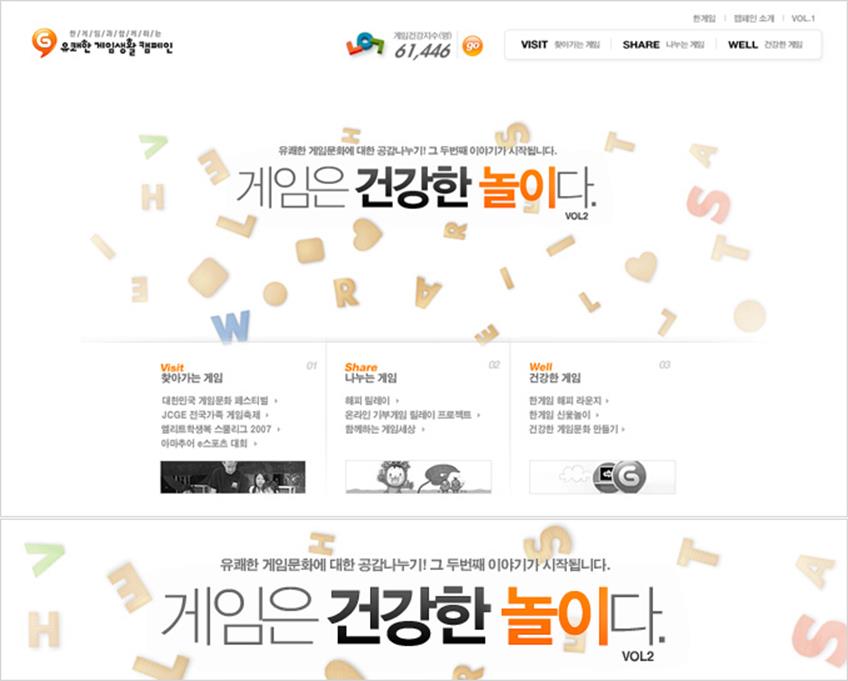
위의 사례를 보면 MAIN카피는 두께 조절과 색상 변형을 통해 아이덴티티 도출과 함께 재미감을 부여했으며 SUB카피는 MAIN카피의 1/4 크기로 일반적인 본문 폰트 크기를 지키고 있다. 이는 핵심문구인 “건강한 놀이”를 강하게 강조하고 SUB 카피는 “건강한 놀이”에 대한 부가적인 설명으로 최소한의 가독성을 유지한 채 MAIN 카피에 상단 중앙에 위치해 안정감과 무게감을 부여 주고 있다. 만약 이 디자인에서 SUB카피가 존재 하지 않았다면 “건강한 놀이” 부분을 제외하고는 글씨가 가늘고 배경에 여백의 범위가 넓어서 위 아래로 뻥 뚫린 듯 불안정한 구도를 연출했을 것이다. 그러나 SUB 카피의 사용으로 위로 뚫릴 수 있는 공간을 막아주고 있으며 두 개가 하나의 묶음으로 인식됨으로써 허전하게 느껴지지 않을 만큼의 충분한 공간을 차지하게 된 것이다.
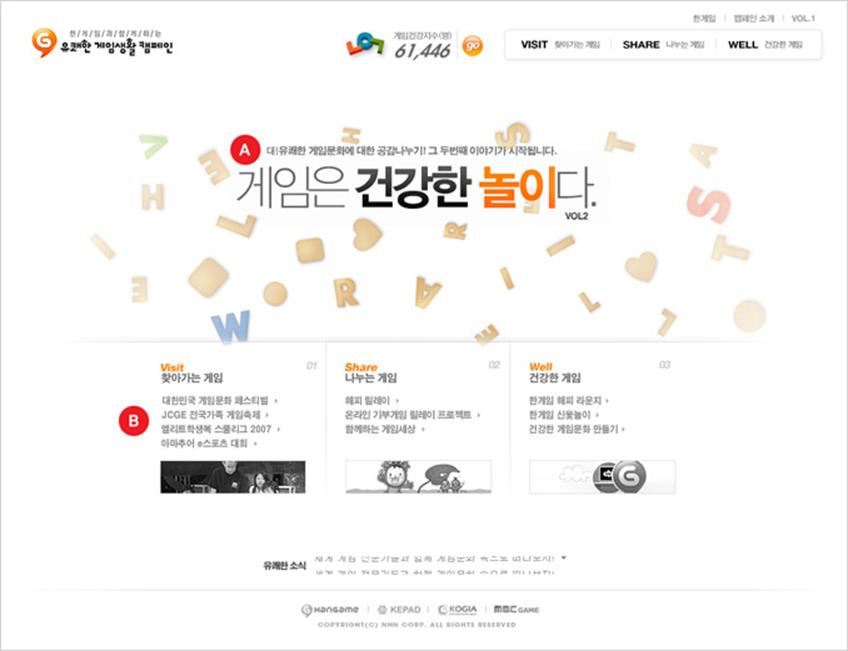
▲ A와 B를 같은 폰트 크기로 통일시킴으로써 안정감을 주고 있다.
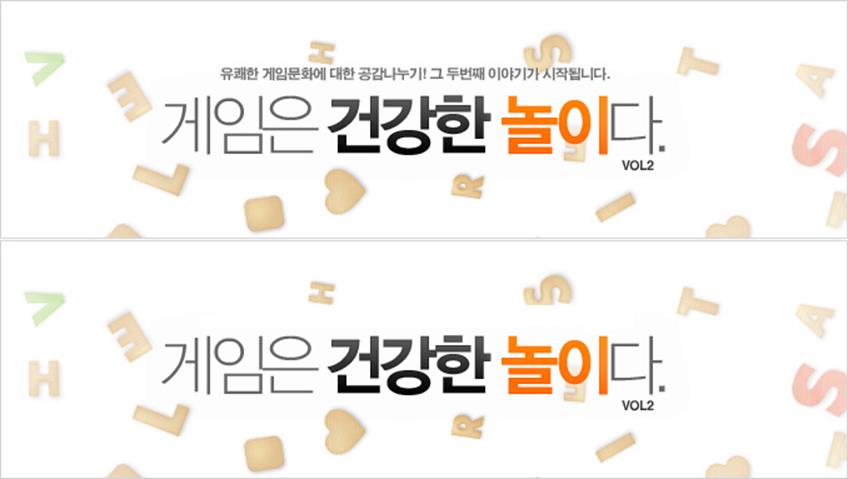
▲ SUB카피의 사용 여부에 따른 안정감 비교
그리고 SUB 카피의 경우 가급적 글자의 장평을 최소 93%이상으로 해 주는 동시에 자간을 -50에서 -120 정도로 설정하는 것이 보다 안정적인 느낌을 줄 수 있는데 장평을 너무 줄이게 되면 가독성이 저해되고 자간을 넓히는 경우는 견고한 느낌을 주지 못해 MAIN 카피에 무게감을 실어주기 보다는 불안정한 화면 디자인을 연출할 수 있기 때문이다.
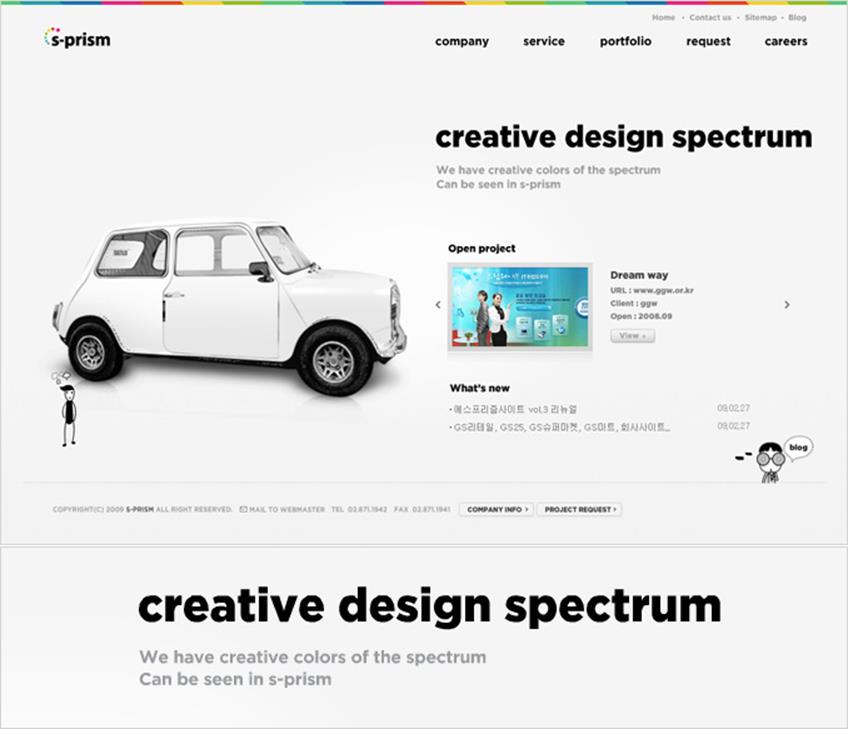
이 디자인 역시 가독성을 최대한 살리는 범위 내에서 SUB 카피의 크기를 지정했으며 MAIN 카피가 굵고 길게 나열 되어 있기 때문에 SUB 카피를 두 의도적으로 두 줄로 나눠 답답함을 피하고 부피감을 부여한 것이 특징이라 할 수 있다.
특히 줄바꿈의 기준을 MAIN 카피 중 “design” 이 끝나는 부분으로 설정해 줌으로써 그리드를 준수해 안정된 구도와 함께 여백의 공간미를 살려 심미성을 높였다.
HEAD 카피와 SUB카피의 색상 조율에 관한 문제
카피의 색상 선택에 있어 가장 우선하여 고려하여야 할 사항은 배경 컬러와 사이트의 아이덴티티 컬러인데, 이 두 가지를 한꺼번에 적용 시키거나 여의치 않은 경우 우선적으로는 배경 컬러에 기준한 컬러 선택이 필수적이라 할 수 있다.
이는 가독성이 무엇보다 우선하기 때문인데, 배경에 이미지를 사용하는 경우 카피와의 조화 문제를 충분히 고려해 이미지를 선택하여야 혼란스런 디자인을 피할 수 있다.
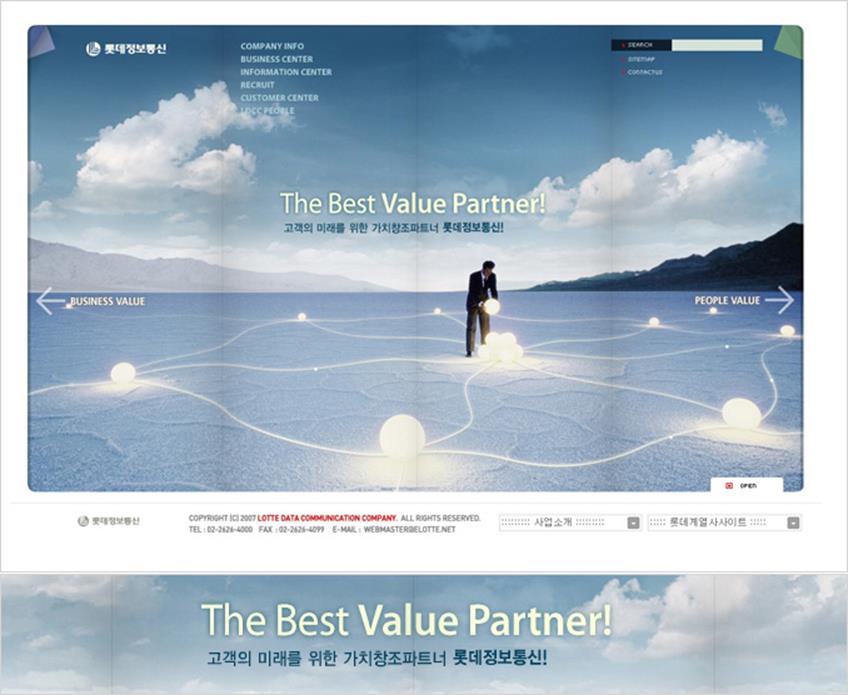
화면 중앙에 위치한 MAIN 카피의 색상은 배경 비주얼에 사용된 빛의 발산 색상과 통일시켜 조화를 이루고 있으며, SUB카피의 색상은 배경과 같은 색상계통인 BLUE를 사용해 MAIN 카피가 드러나 보이도록 유도하고 있다. 또한 SUB 카피의 경우 배경보다 어두운 톤의 색상을 사용함으로써 가독성을 전혀 헤치지 않으면서도 MAIN 카피와는 색상의 대비를 이뤄 주연과 조연의 관계를 확실히 하고 있는 것이 특징이다.
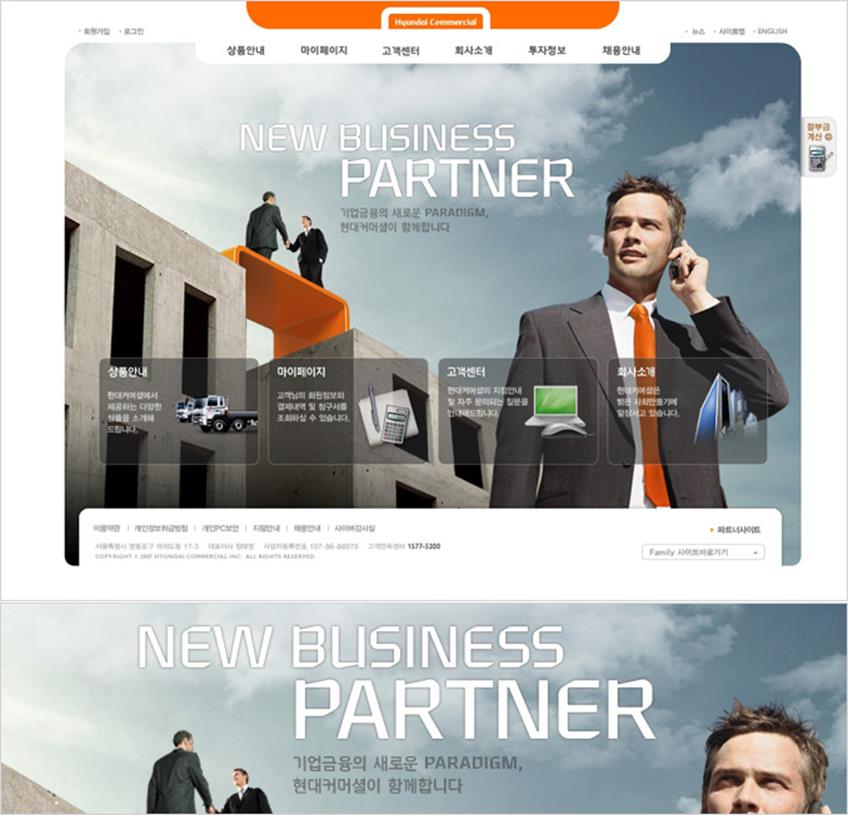
이 디자인 역시 앞의 예와 마찬가지로 MAIN 타이틀은 WHITE 색상으로 하여 구름과 같이 어울릴 수 있는 컬러를 선택했으며 SUB타이틀은 배경 색상과 같은 계열의 색상에서 색상을 진하게 하여 가독성을 헤치지 않고 있다. 이를 통해 MAIN 카피와 SUB카피의 대비효과로 MAIN 카피에 강한 임펙트를 실어주고 있는 모습을 발견할 수 있다.
또한 배경의 구름과 MAIN 카피로 사용된 글자의 색상 톤이 비슷해 SUB 카피의 색상과 같은 색상의 외곽라인을 사용해 임펙트를 강화 시켰다.
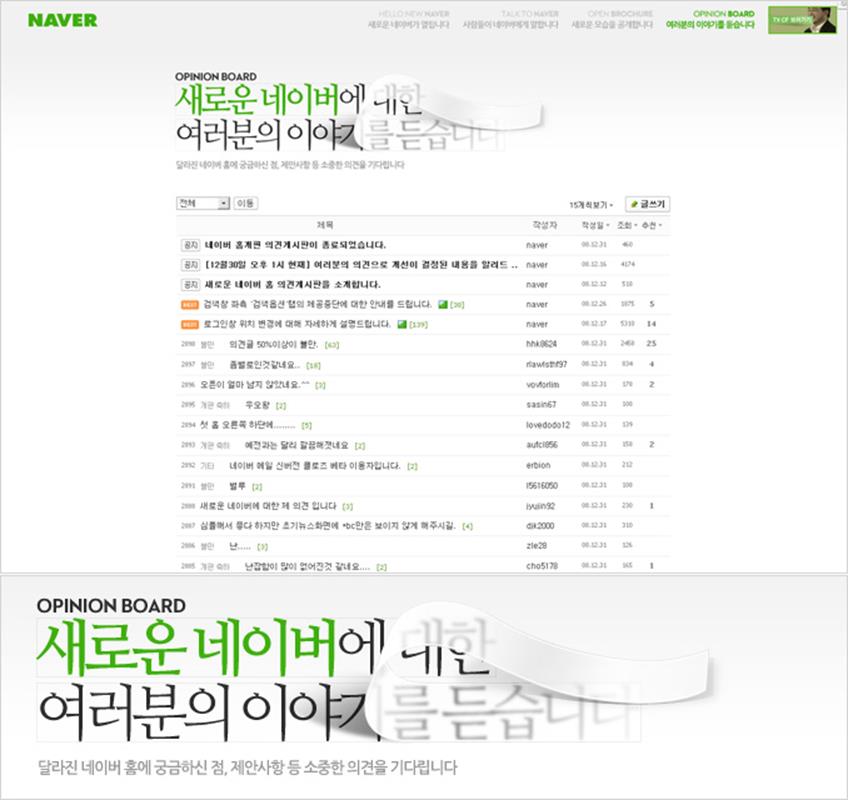
위 사례는 2009년 네이버의 사이트 개편을 맞아 프로모션용으로 제작되었던 사이트 디자인으로서 네이버의 아이덴티티 컬러를 강조해 MAIN 타이틀에 적용 시켰다.
MAIN 카피 안에서도 명도가 높은 GREEN과 채도가 낮은 BLACK에 가까운 GRAY를 사용해 강한 대비 효과를 발생시켜 “새로운 네이버”를 강조하고 있으며 SUB 카피는 MAIN 카피보다는 훨씬 옅은 GRAY 색상을 사용해 가독성을 잃지 않는 범위 내에서 장식적인 요소로 작용하고 있다.